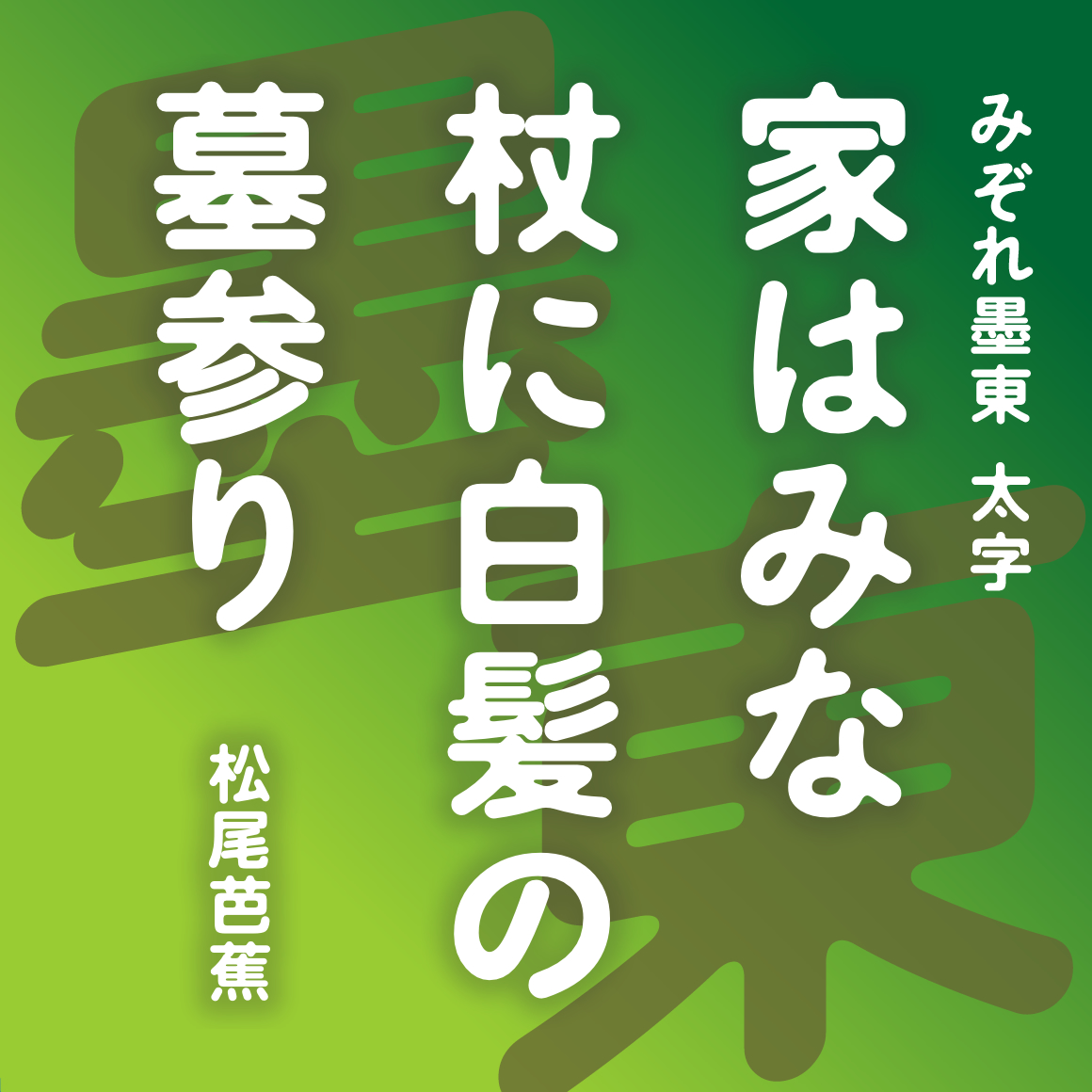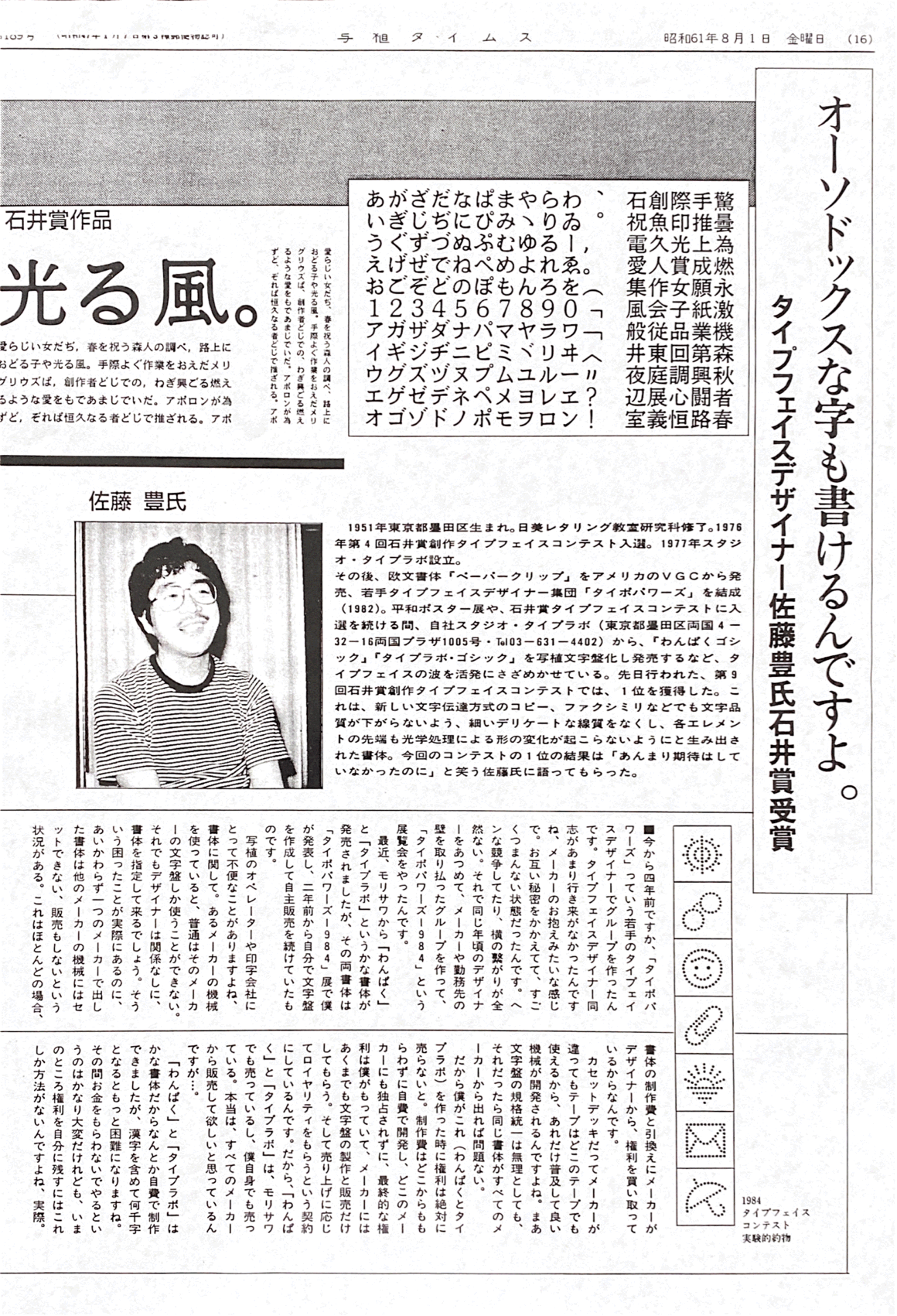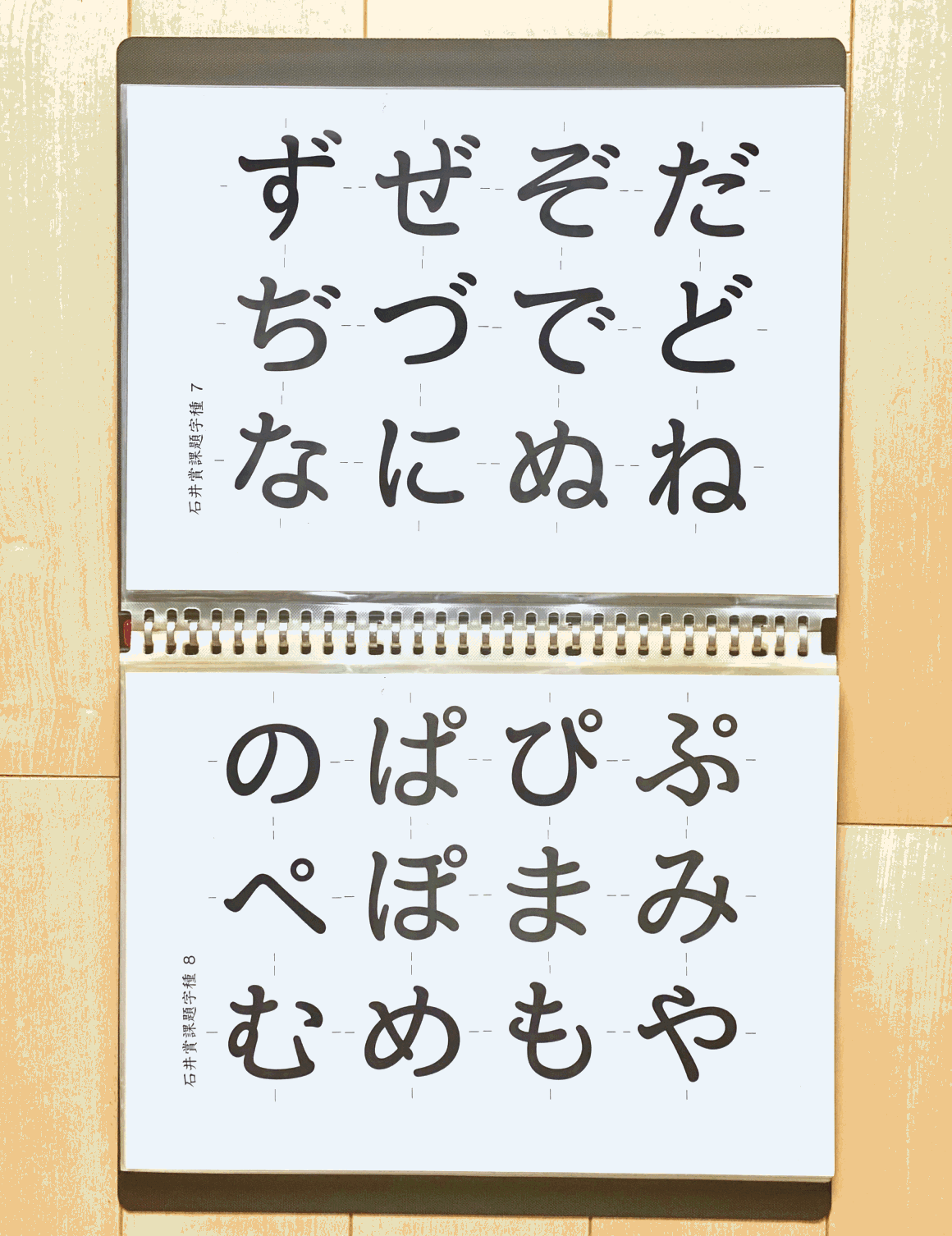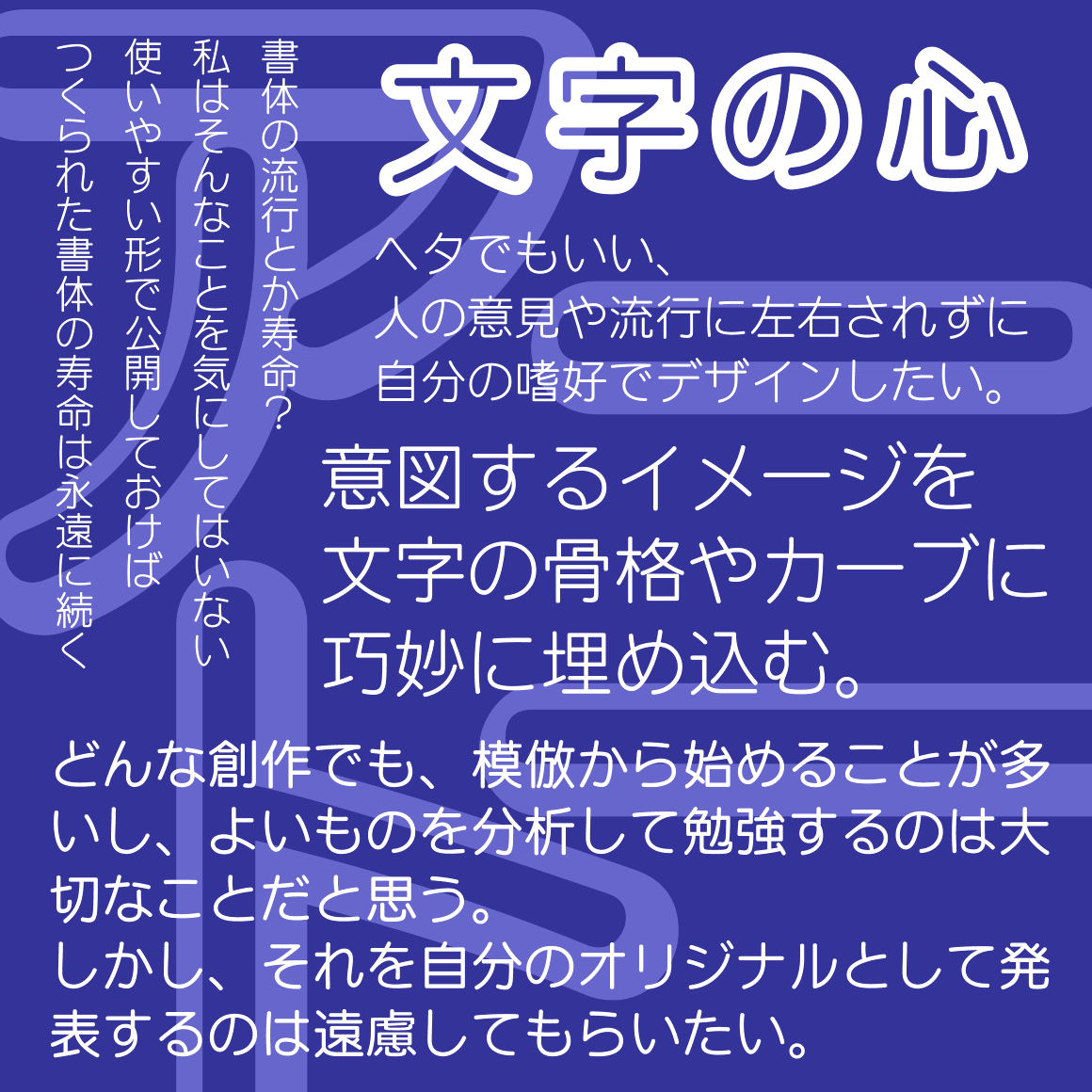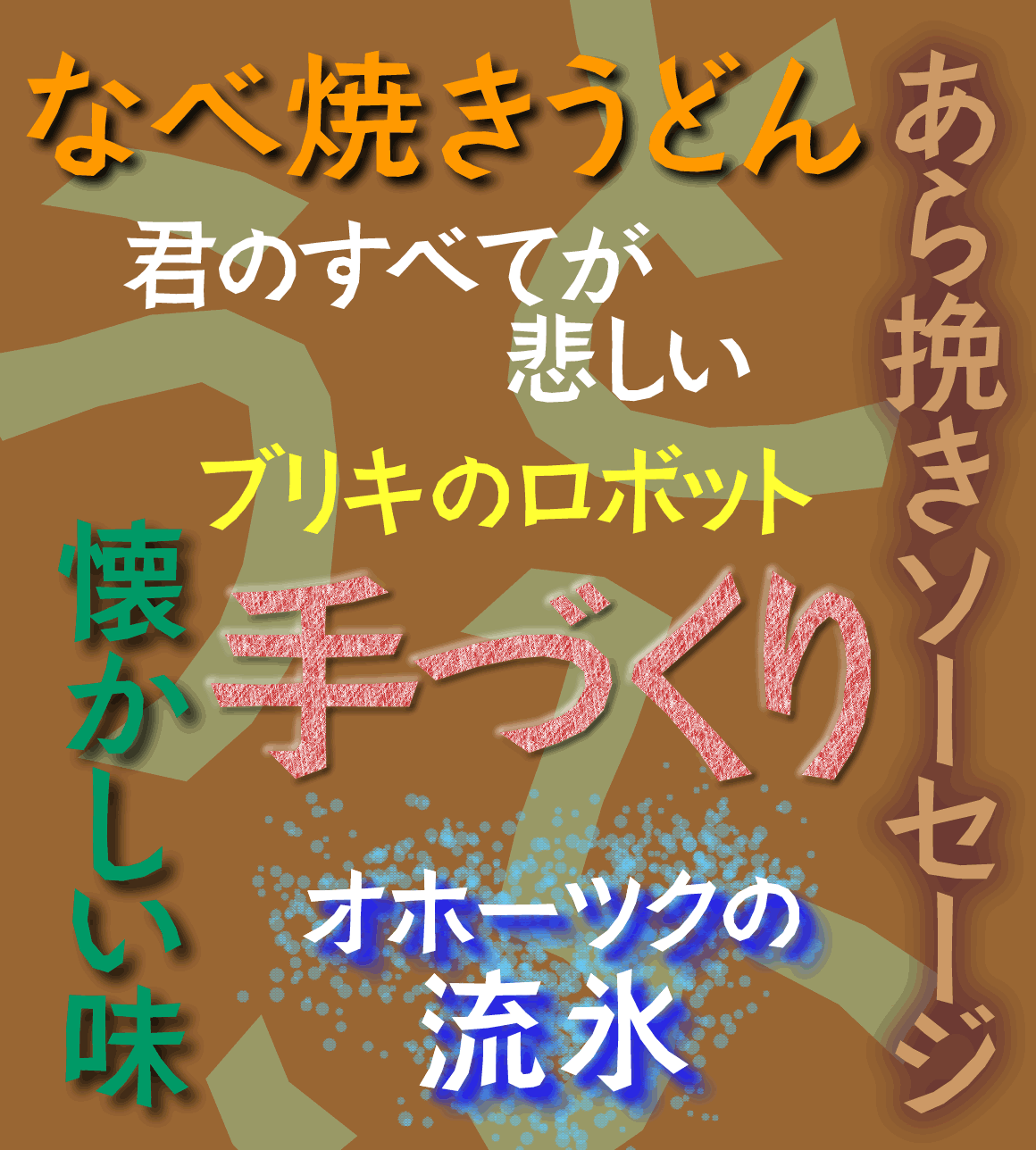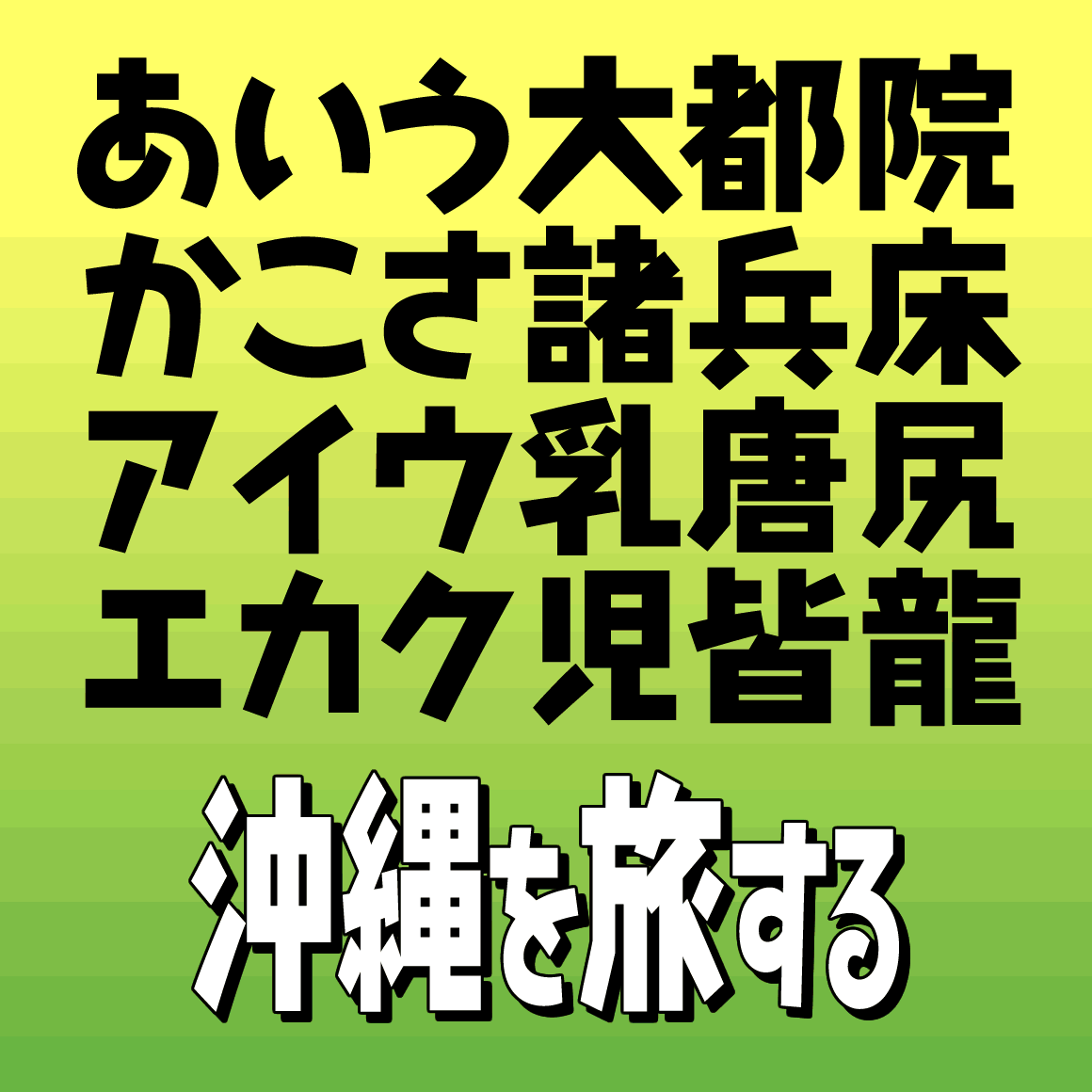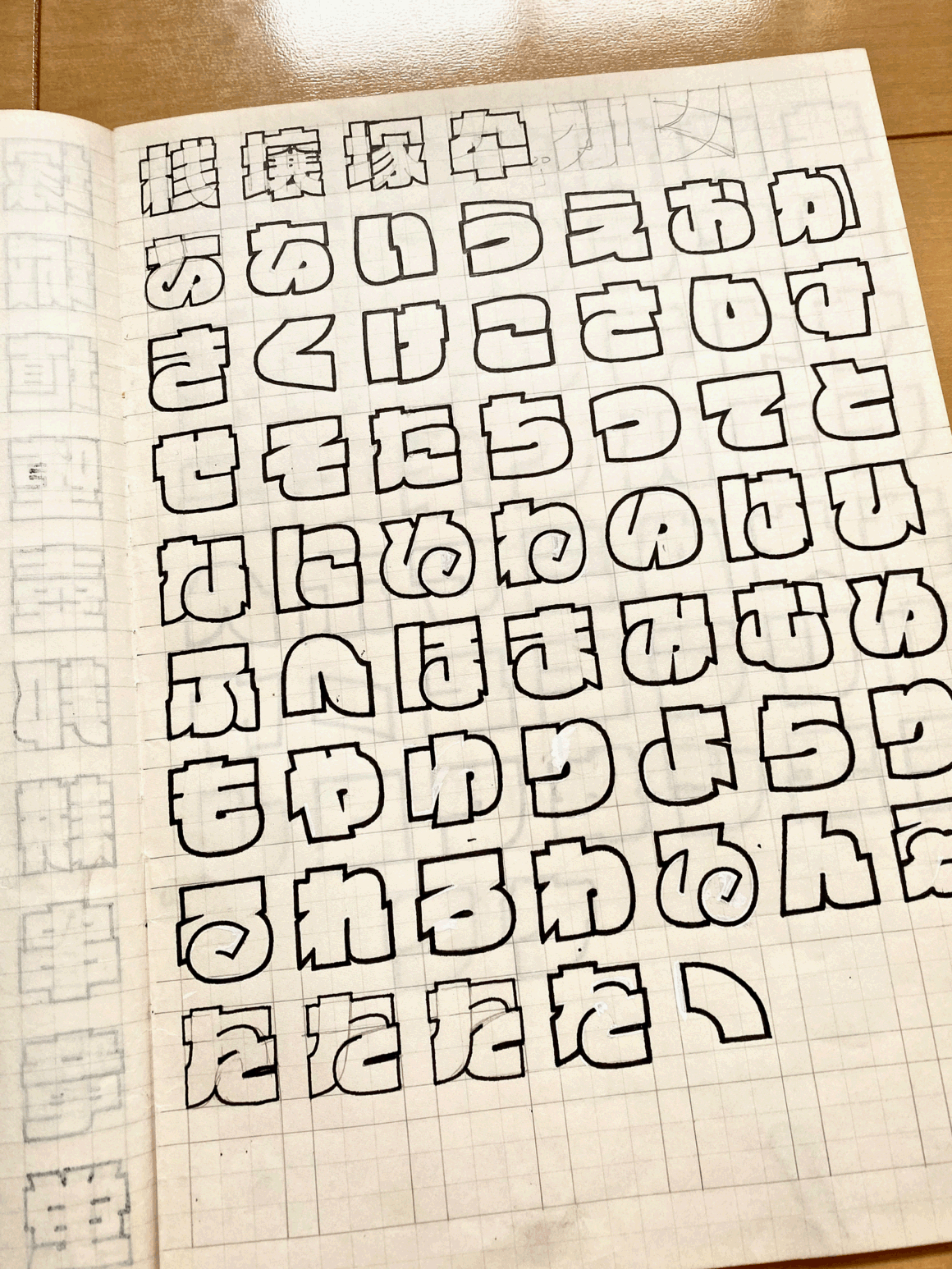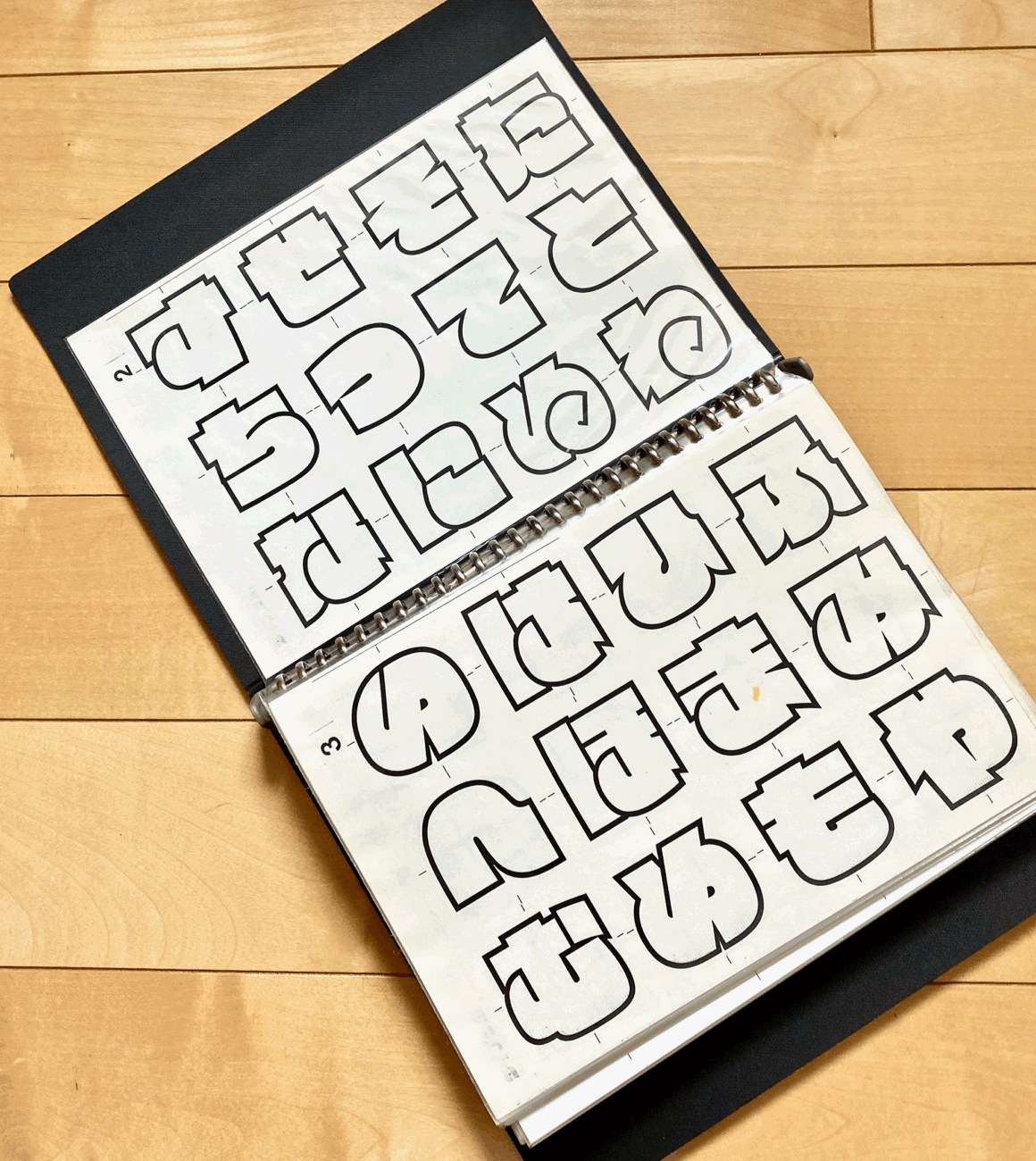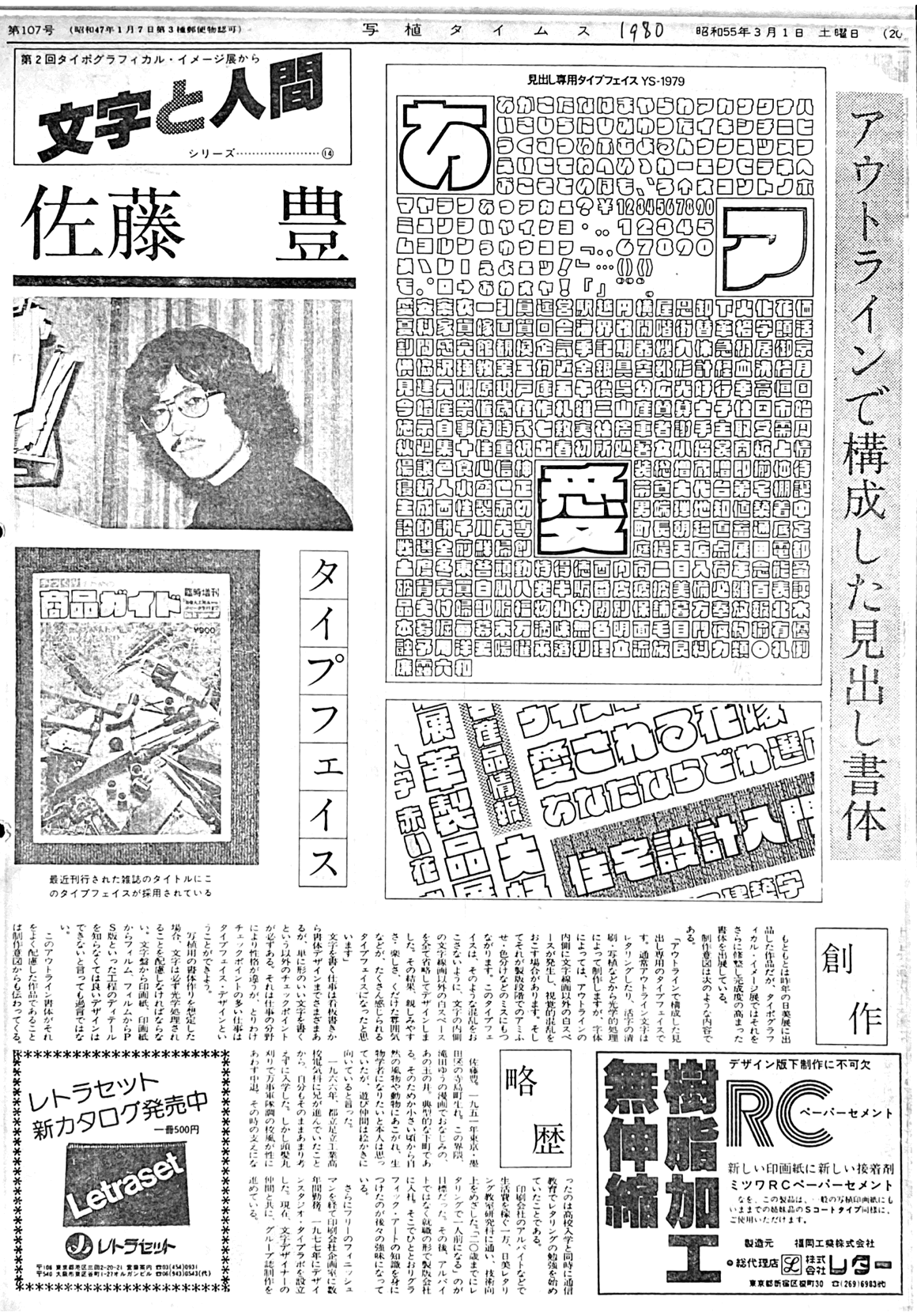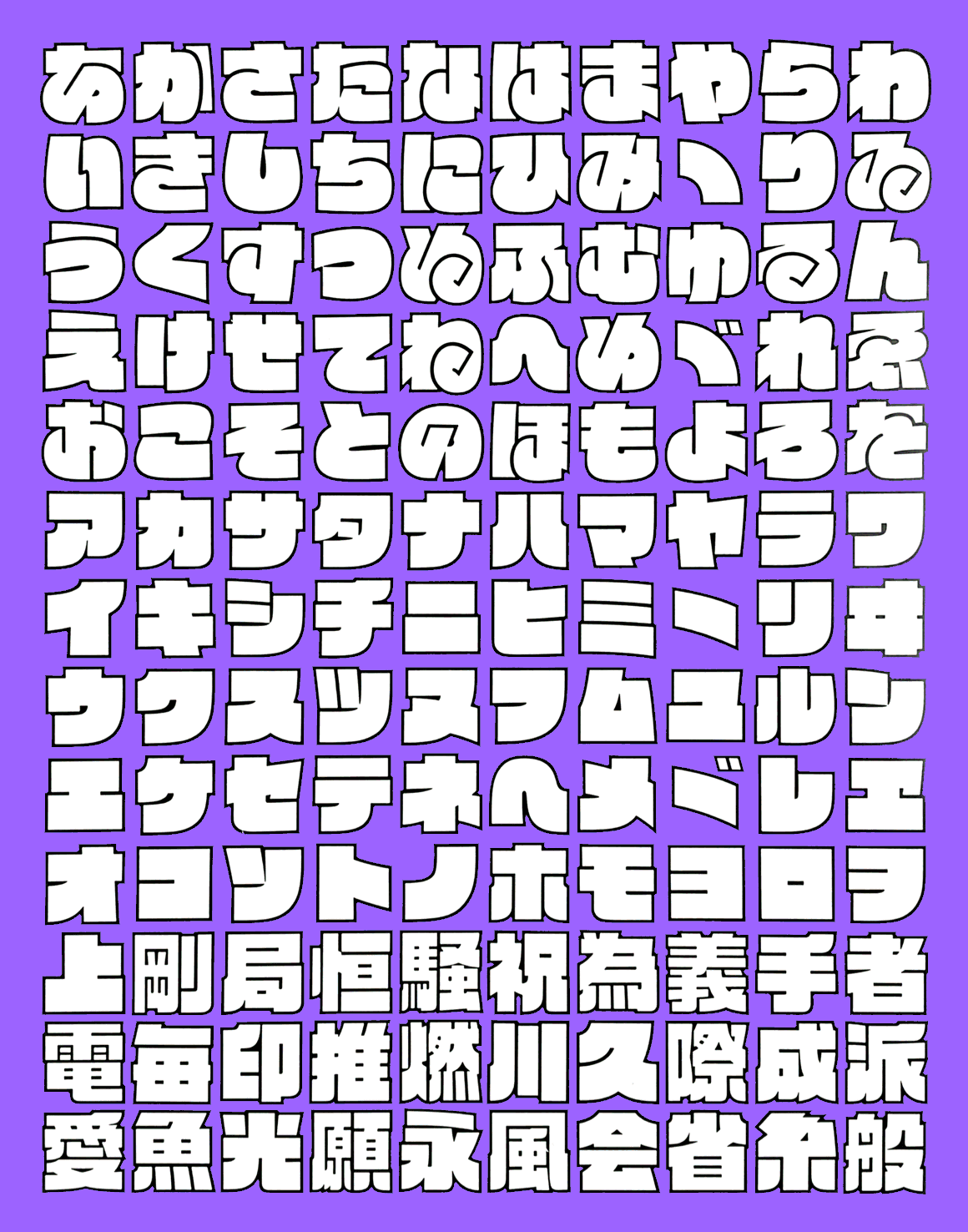
2019年に発表したレラ-4と墨東レラ-4をベースに開発。
線画の交点に丸みを与えて、日本の湿度やしっとりとした感覚を表そうとした。
言葉や想いが、相手の心に柔らかく優しく伝わる書体になった気がする。
2009年に発表したルイカ書体をベースに開発した丸ゴシック書体。
他のかな書体と組み合わせたフォントは、2020年から順次頒布した。
ある時期、かな書体ばかりデザインしていました。
漢字は中国から、英数字は欧米から、伝わってきたもの。それなら、日本発祥の「ひらがなカタカナ」を、私が心をこめてデザインしてやろう……という考えだったのでしょう。
しかし「ひらがなカタカナ」だけでは、あまり実用的ではありません。
やはり、漢字も英数字もみんな揃った総合書体の方が便利です。
ということで、これまでデザインしてきた「わんぱく・ニュータイプラボゴシック・墨東・ハッピー」などの、かな書体と組み合わせる基本総合書体として、ルイカをデザインしました。
他のかな書体と組み合わせたフォントは、2010年から順次頒布していく予定です。
10代のころから文字を描いて収入を得ていました。25〜35歳のころ、ロットリングという筆記具を使って、イラストマップやグリーティングカード用の小さな文字をずいぶん描きました。そのころ描いた文字をみんなに使ってもらえるように、昔を思い出しながら作りました。
ペン習字の書体のような気取ったものではなく、もっと親しみやすく読みやすく、この書体を使う人の気持が素直に相手に伝わるようにデザインしたつもりです。
この書体が完成する日をとても楽しみにしていた、大切な友人が逝去した1998年の9月を忘れることのないように、書体名を「セプテンバー」としました。
そして2016年の秋、セプテンバー書体は新しく生まれ変わりました。
新たに太いデザインを2種作成しウェイトが4種類に増え、NEC特殊文字やIBM拡張文字も使用できます。
ある程度、大きく使ってほしい書体です。直線だけを使用して、切り絵とか木版画のような味わいでデザインしてあります。小さいサイズではこの書体の面白さが発揮できません。
まだ誰も見たことのないオリジナルの日本語書体を、原字を描かずに直接パソコン上でデザインすると、どの程度の時間がかかるのか試してみようと、変な動機で作り始めました。
1994年秋から1998年6月まで、ひらがな・カタカナ・欧文・記号・漢字など約8700の文字デザインを完成させるのに一人で3年半費やしました(途中で大幅なデザイン変更などがありましたが…1998/06
記)。
↑このときは完成したと思ったのですが、日がたつにつれ直したい部分が見えてきてしまい、この後数回の修整を重ね、2001年の秋やっと公開できるような状態になりました。
満7年もかかってしまったんですね(ふ〜)。
そして2023年、太いウェイトも作り拡張漢字も追加したNewバージョンが完成。
これで、あられ書体は完成…ということになります。
自分の書体に対する考え方が変な方向に行っていないか、狭くなったりしていないかを確かめる健康診断的な意味合いもあって、このようなコンテストに出品しています。まぁ、そこそこ健康だったようですね…
この雰囲気のデザインは、かなり前から研究していたもので、第3回(1990)にも同じコンセプトの別書体を出品しました。その時は選外になりましたが、その書体のかな文字部分は、のちに「墨東」として世に出しました。
10年前の石井賞受賞書体では、明朝体デザインに対する私なりの考えを明示しましたが、今回のこの書体は、ゴシック体デザインに対する私なりの答えです。
明朝体一辺倒の文芸物の文字組に、こんなゴシック体が使われてもイイと思うのですが…
出品時の制作意図
欧文書体に感化されたデザインではなく、漢字や仮名文字を筆記する時の自然な形を尊重しました。読みやすく、そして美しく情感のある本文用ゴシック書体です(出品作品PDF)。
・選評
さらりとデザインされている様で奥の深い書体である。縦線、横線の線率から見るとゴシック体であるが、楷書の古典を取り入れることによってヒューマニックなイメージとなり、組の流れにつながって読みやすい。懐の広い書体が多い今日、懐のしまったデザインに作者のセンスが伺える作品である。
・勝井三雄氏の選評より抜粋
文字はコミュニケーションのための最もベーシックなソフトであって、長い歴史に育まれた普遍性を獲得することによって、社会的な存在として機能しています。
一方、個人においても誰もが非常に長い時間、文字と付き合っている。しかし、そのためにたとえば書き文字には、それぞれのクセ、個性というものを強く認めることができる。つまり文字には、そのような社会史と個人史に由来する二面性があると思います。
新しい書体のデザインにおいても、ある共通のルールや品位といったものがまず求められます。と同時に、作者の肉体性を強く感じさせる表現の発露が欠かせません。しかもそれは、単なる作者のクセではなく、意図が明確に意識化されていなければならない。こうして生み出されたクォリティと個性を伴わせ持った書体こそが、私たちに強いインパクトを与える書体にほかなりません。
そのような意味からすると、今回の和文部門は非常にレベルが高かったといえます。多くの作品が「組み」としての完成度、読みやすさを十分意識しています。一方、書体としてはオーソドックスなものとオリジナリティを強調した作品に、かなりはっきり分れたと思います。その中で金賞の「あさがを」は、右上がりのゴシック系書体ですが、これまでのゴシックにはない柔らかさと品位があり、切り口の斬新さにおいて抜きん出ていながら、誰もが納得するクォリティを備えています。
・小塚昌彦氏の選評より抜粋
やはりタイプデザインには独創性とともに、共通の認識を伝達するビジブルコミュニケーションの機能が根底に必要でしょう。その認識がかなり定着してきた感じがありますね。
なかでも書をタイプフェイスとしてアレンジする試みや、自分の手で書くという動作、雰囲気から発想した作品が非常にふえる傾向にあります。
私は「タイプフェイスは目で見る言葉である」という考え方がとても好きなのですが、人間が書くという行為を基本にしながら、書体としての統一性をもった「目で見る言葉」として表現し得た、金賞の「あさがを」の作者はかなり修練を重ねた良いスキルを持ったデザイナーだと思います。
コンテストの出品仕様はアナログだったが、デジタル制作したので何度も修正を繰り返して完成度を上げた…。
などの利点が考えられる。
現在ほとんどの長文横組が、本来は縦組用にデザインされた書体を使用しているのではないかと思う。
そして今のままでは、いつまでたっても長文横組が定着しないと考え、この書体を制作した。
点、丸、カンマ、ピリオドは半角でも全角でも使用できる。両かな、数字、音引、(「<は、半角前つきにしてある。
両かなを半角にしたことで奇数級数の印字に問題が起きるが、半角後つきの両かなも制作し、組数字のように使用すれば解決できると思う。
●最初は、もうすこし個性的なデザインだった(ラフスケッチ〜テスト文字盤用版下など)。
写植用の文字盤まで作りテスト印字を重ねて検討したが、最終的にはおとなしい地味なデザインで出品した…。
初めての両がな、漢字とも揃った総合書体のデザイン。
写植文字盤を自作し、第3回石井賞に応募したが見事に落選。
小中学校時代の私のニックネーム「ゆたんぽ」から命名、何年も何回もやりなおした書体だが、いま見ると稚拙で幼く感じる。
この頃から本格的に書体の研究が始まりました。